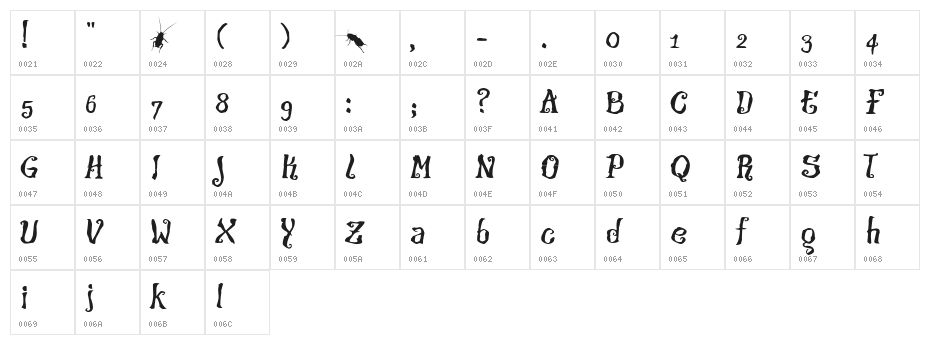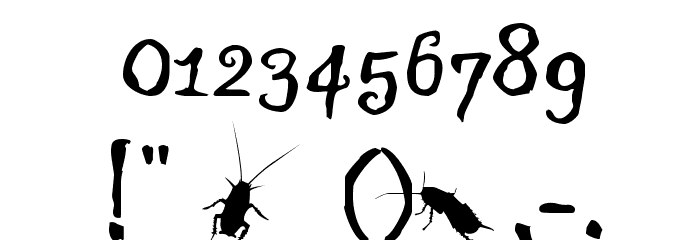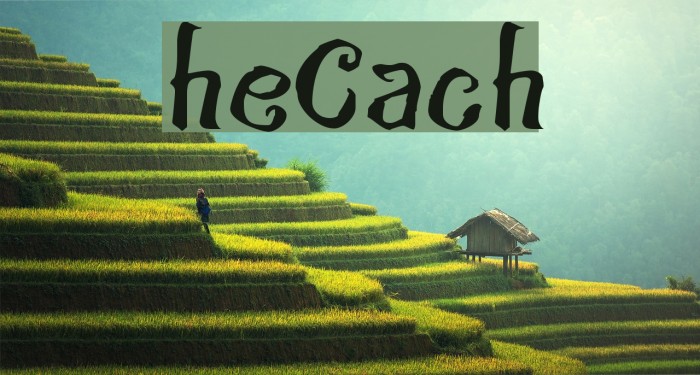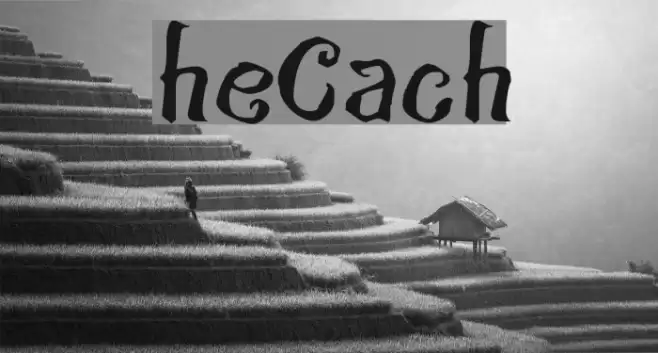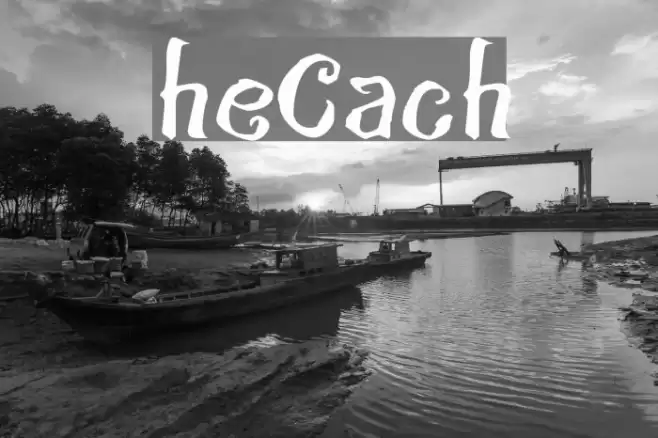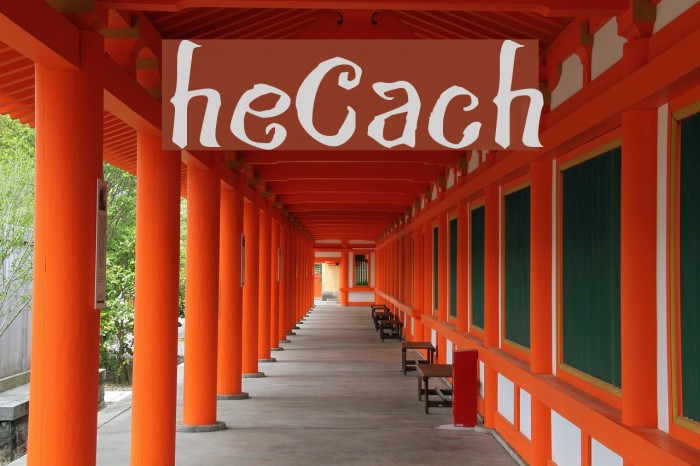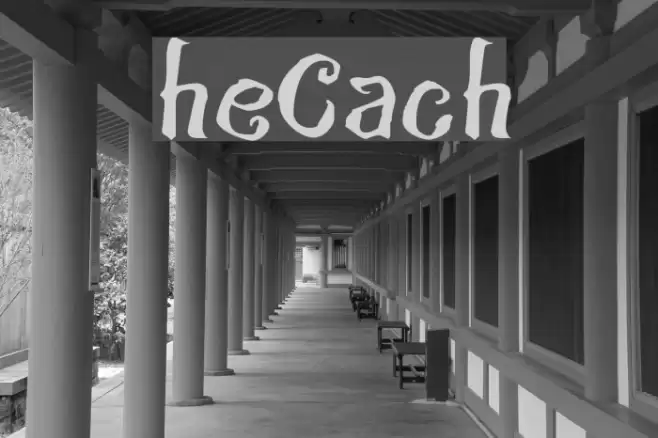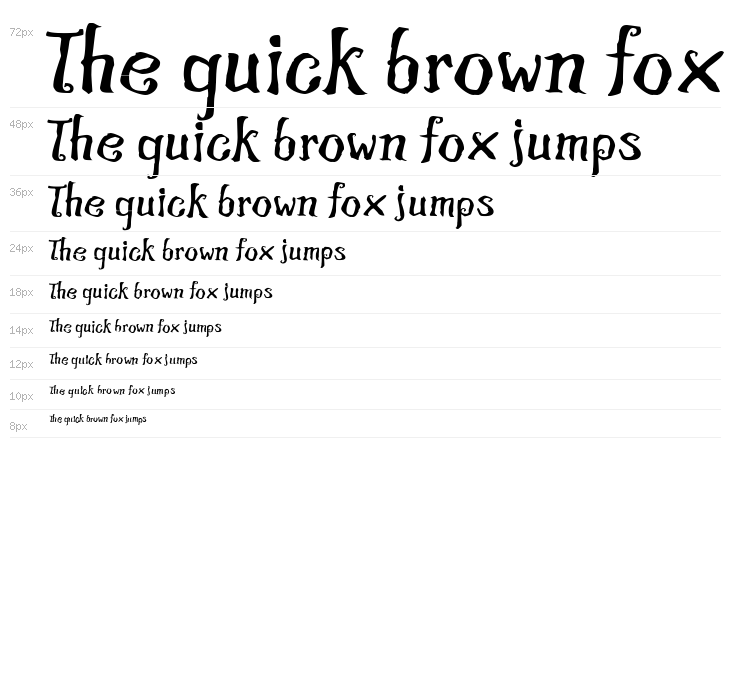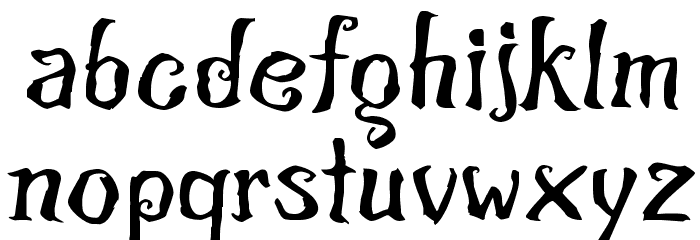
theCroach Font
| Общий стиль | Playful, Whimsical, Hand-drawn |
| Рекомендуемые проекты | Ideal for children's books, playful branding, creative posters, and whimsical invitations. |